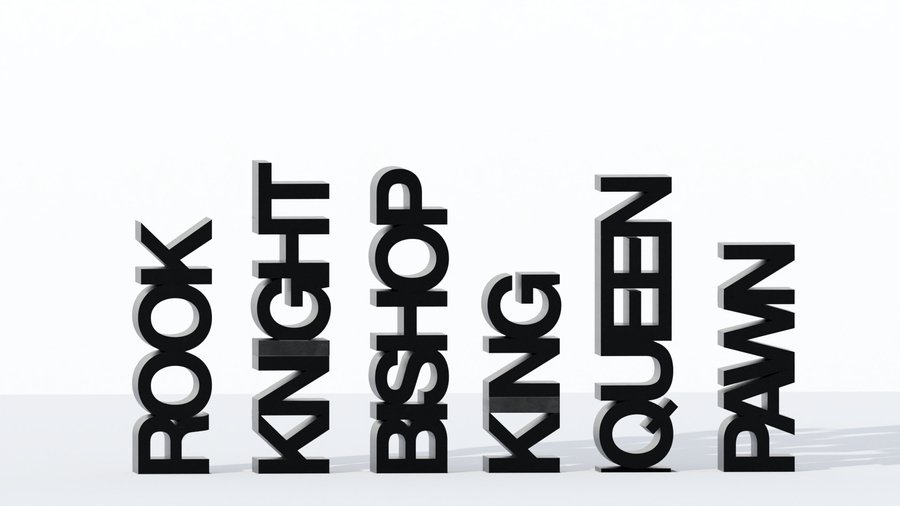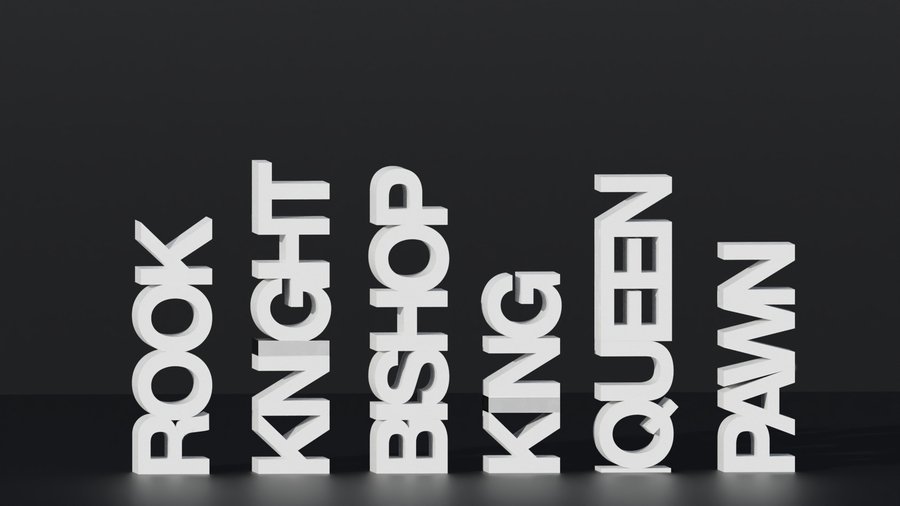
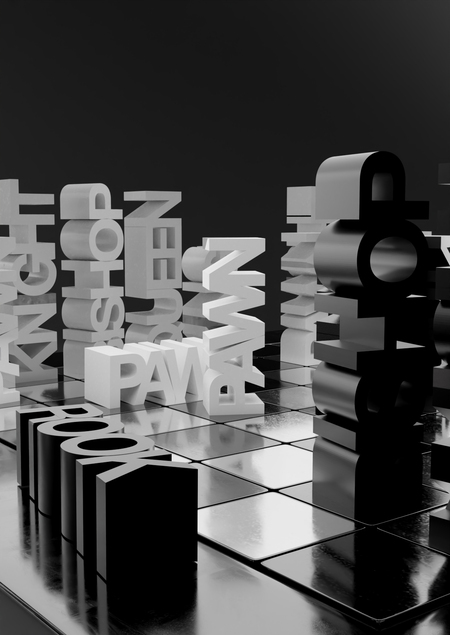
Helvetica fonts Chess — это размышления по поводу языка и визуальной формы. Для школы Баухауса было важно, что форма следует за функцией. Я пытаюсь понять, как форма может точнее передать смысл, если она — буквально слово.
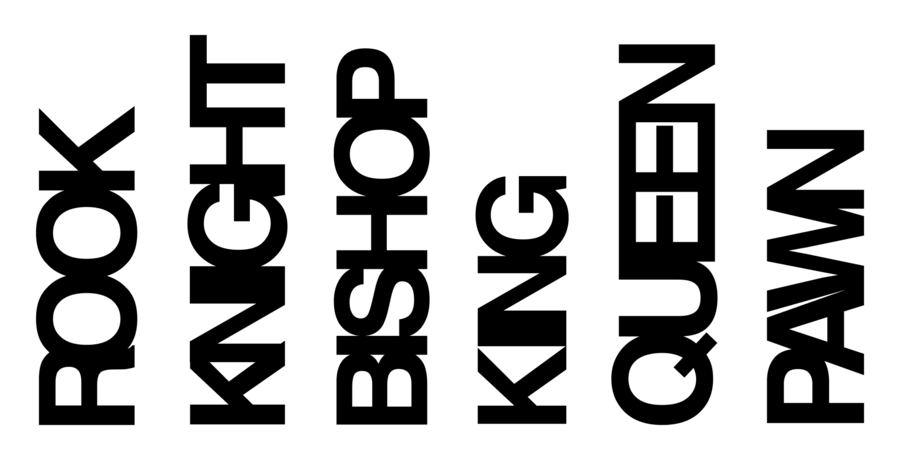
Что если взять Гельветику и на её основе создать шахматы. Вместо фигур-символов будут слова, буквально означающие игровые названия.